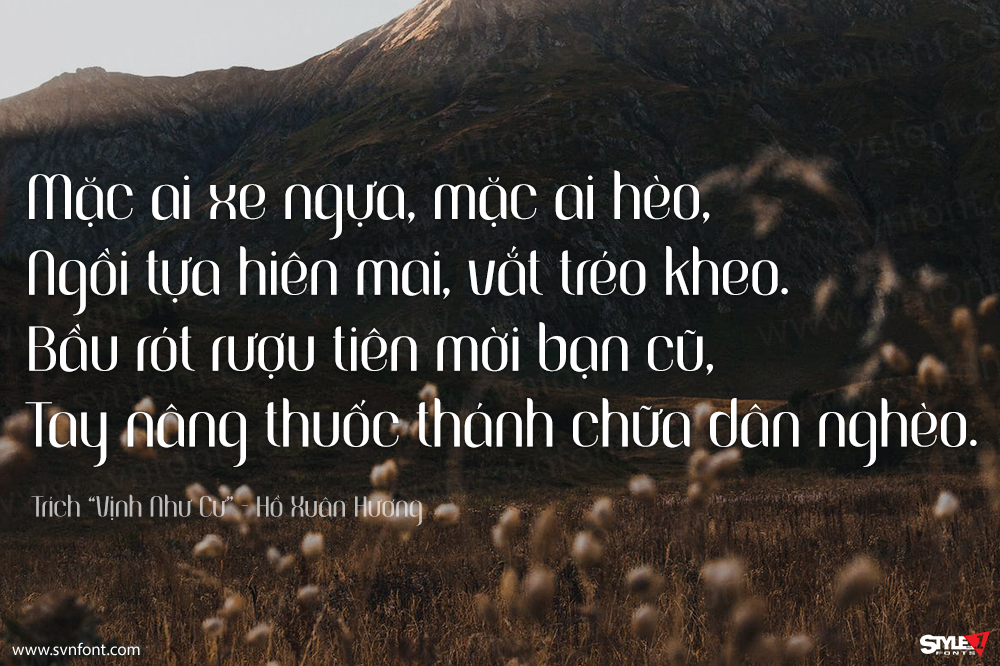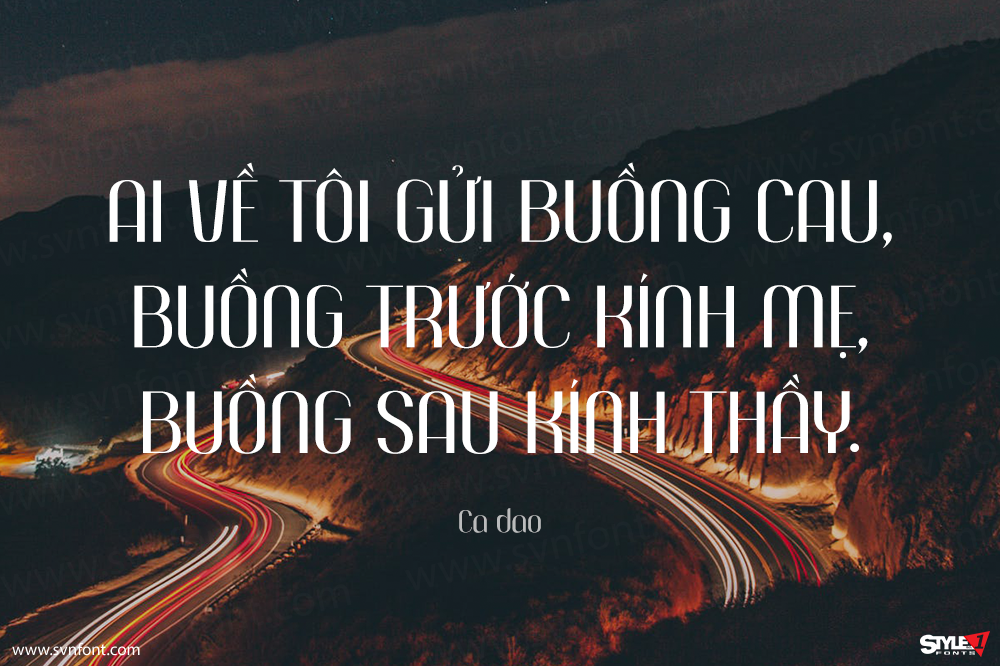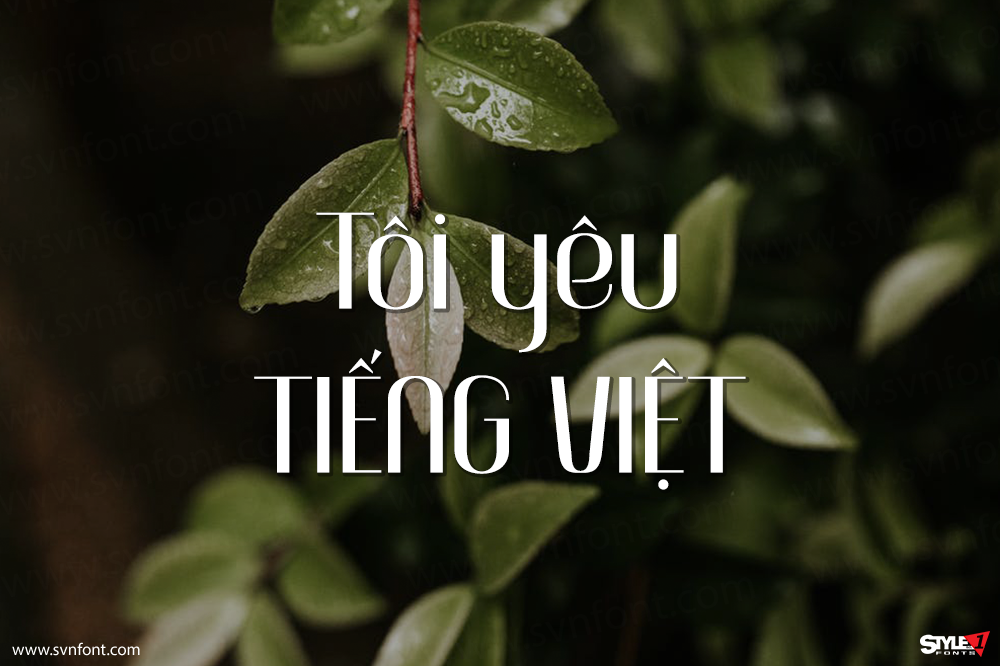
Fashion là một typeface sans-serif có độ tương phản cao, được kết hợp những đường thẳng với những đường cong mạnh, tạo sự thanh lịch, sang trọng nhưng mềm mại. Font thích chợp cho các thiết kế về thời trang, mỹ phẩm, banner, logo…
Nhà thiết kế: Zamroni Hamzah
Nhà phát hành: Sensatype